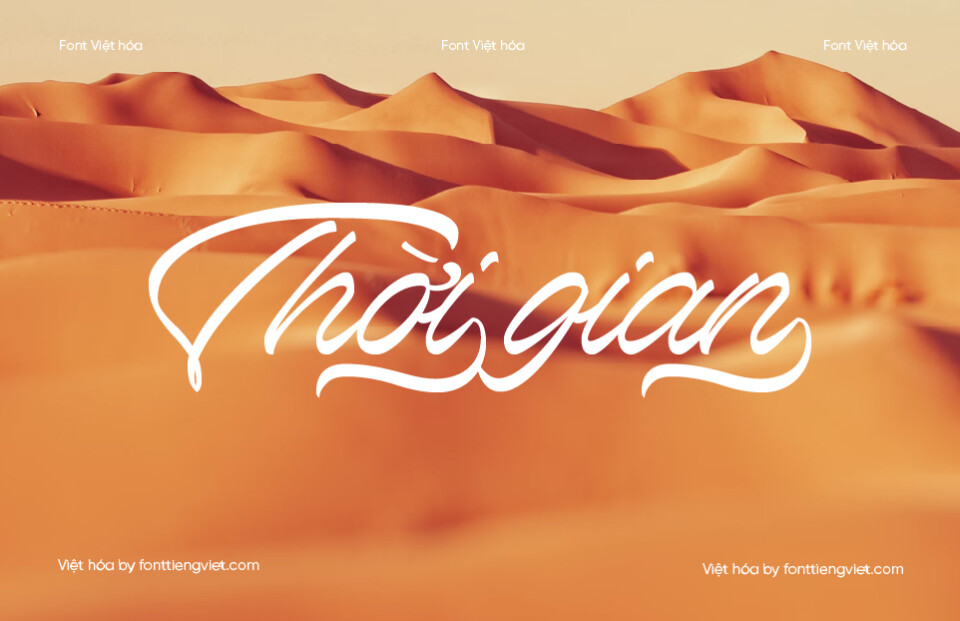
Khám Phá Sự Sang Trọng Của Font Việt hóa 1FTV VIP Roadly Hezarttest Cho Thiết Kế Đồ Họa Tuyệt Vời
Trong thế giới thiết kế đồ họa, việc lựa chọn Font Chữ không chỉ là một quyết định thẩm mỹ mà còn là yếu tố then chốt quyết định tính chuyên nghiệp và thông điệp của tác phẩm. Gần đây, giới mộ điệu đã không ngừng tìm kiếm và ca ngợi siêu phẩm Font Việt hóa 1FTV VIP Roadly Hezarttest. Đây là một trong những bộ font cao cấp, được Việt hóa tỉ mỉ, mang đến sự lựa chọn hoàn hảo cho những dự án đòi hỏi sự sang trọng, độc đáo và tính nghệ thuật cao. Dù bạn là học sinh, sinh viên đang chuẩn bị cho các dự án lớn, hay là nhà thiết kế chuyên nghiệp, việc nắm bắt được ưu điểm của bộ font này sẽ giúp nâng tầm chất lượng sản phẩm của bạn lên một đẳng cấp mới.
Đặc Điểm Nổi Bật Của Font Việt hóa 1FTV VIP Roadly Hezarttest: Sự Kết Hợp Giữa Nghệ Thuật và Chuyên Nghiệp
Bộ font 1FTV VIP Roadly Hezarttest được biết đến là một phông chữ script (viết tay) với nét cọ mạnh mẽ, phóng khoáng nhưng vẫn giữ được sự tinh tế cần thiết. Sự “VIP” của nó không chỉ nằm ở tính thẩm mỹ mà còn ở chất lượng Việt hóa tuyệt vời, đảm bảo hỗ trợ đầy đủ các ký tự tiếng Việt, dấu thanh, và kerning (khoảng cách giữa các chữ) được căn chỉnh hoàn hảo. Điều này đặc biệt quan trọng đối với các dự án in ấn tại Việt Nam, nơi mà việc sai sót trong hiển thị dấu tiếng Việt có thể làm hỏng toàn bộ thiết kế.
Roadly Hezarttest mang lại cảm giác cá nhân hóa và thủ công, rất thích hợp cho các ấn phẩm mang tính chất cá nhân, thư mời, logo thương hiệu cao cấp, hoặc bìa sách. Sinh viên các ngành thiết kế, truyền thông thường tìm kiếm những font chữ độc đáo như thế này để tạo dấu ấn khác biệt cho các bài tiểu luận, báo cáo tốt nghiệp, hay các dự án truyền thông học đường quan trọng. Tính độc quyền và sự khác biệt mà font này mang lại giúp tác phẩm nổi bật giữa hàng ngàn sản phẩm khác.
Ứng Dụng Đa Dạng Của Roadly Hezarttest Trong Môi Trường Học Thuật và Thiết Kế
Mặc dù là một font “VIP” mang phong cách nghệ thuật, Roadly Hezarttest lại có ứng dụng rất rộng rãi, đặc biệt là trong các dự án của học sinh, sinh viên cấp 3 và các cấp. Các ứng dụng tiêu biểu bao gồm:
- Thiết kế Kỷ Yếu Tốt Nghiệp: Giúp tiêu đề kỷ yếu, tên trường hoặc các trích dẫn trở nên nổi bật và lãng mạn hơn.
- Poster và Banner Sự Kiện Trường Học: Tạo ra các thông báo sự kiện, hội trại, hay cuộc thi mang tính chất nghệ thuật và thu hút.
- Đồ Án Tốt Nghiệp: Sử dụng làm tiêu đề chính cho các bìa đồ án mỹ thuật, thiết kế thời trang, hoặc kiến trúc.
- Thương Hiệu Cá Nhân (Branding): Hỗ trợ sinh viên khởi nghiệp xây dựng logo và bộ nhận diện thương hiệu đầu tiên.
Việc sử dụng một font chữ đẹp, độc đáo như thế này cũng giúp học sinh, sinh viên thể hiện được sự đầu tư nghiêm túc và gu thẩm mỹ của mình, qua đó có thể đạt điểm cao hơn trong các môn học liên quan đến trình bày và thiết kế.
Lợi Ích Của Font Chữ Việt Hóa Chất Lượng Cao Đối Với Các Dự Án Giáo Dục
Chất lượng “Việt hóa” là yếu tố then chốt biến một font chữ quốc tế thành công cụ đắc lực cho người Việt. Khi sử dụng font đã được Việt hóa kỹ lưỡng, các bạn học sinh, sinh viên sẽ không phải lo lắng về các lỗi hiển thị dấu tiếng Việt thường gặp như: dấu hỏi và dấu ngã bị lệch, hoặc khoảng cách chữ bị dính sát vào nhau. Bộ Font Việt hóa 1FTV VIP Roadly Hezarttest đảm bảo rằng mọi văn bản đều mượt mà, dễ đọc, và duy trì được tính thẩm mỹ ban đầu của nhà thiết kế font chữ. Sự chuyên nghiệp này là điều mà các giáo viên và hội đồng đánh giá luôn mong đợi ở các bài dự thi hoặc báo cáo cuối khóa.
Đặc biệt đối với các kỳ thi tốt nghiệp THPT hoặc các bài kiểm tra quan trọng yêu cầu trình bày chuyên nghiệp, mặc dù không được phép sử dụng các font trang trí như Roadly Hezarttest trong văn bản chính thức, nhưng kiến thức về typography và khả năng lựa chọn font phù hợp cho các tài liệu phụ trợ (ví dụ: poster quảng bá chương trình thi, hướng dẫn học tập) là một kỹ năng giá trị.
Roadly Hezarttest cũng là lựa chọn tuyệt vời cho các bạn trẻ đang học thiết kế hoặc muốn mở rộng portfolio cá nhân. Các dự án sử dụng font chữ này thường được đánh giá cao hơn về mặt thẩm mỹ và sự đầu tư chi tiết. Đây chính là lợi thế cạnh tranh lớn cho những ai đang tìm kiếm cơ hội học bổng hoặc việc làm sau khi tốt nghiệp.
Tóm lại, Font Việt hóa 1FTV VIP Roadly Hezarttest là một tài sản quý giá trong thư viện thiết kế của bất kỳ ai theo đuổi sự hoàn hảo. Từ các dự án học đường cấp cao cho đến các ấn phẩm thương mại đòi hỏi tính nghệ thuật, sự sang trọng và chất lượng Việt hóa đỉnh cao của nó đều không làm người dùng thất vọng. Việc đầu tư và khai thác hiệu quả bộ Font Chữ này sẽ mở ra cánh cửa sáng tạo không giới hạn, giúp các tác phẩm của bạn luôn chuyên nghiệp và thu hút. Đừng ngần ngại khám phá và tận dụng tối đa ưu điểm của Roadly Hezarttest để tạo nên những sản phẩm thực sự đẳng cấp.